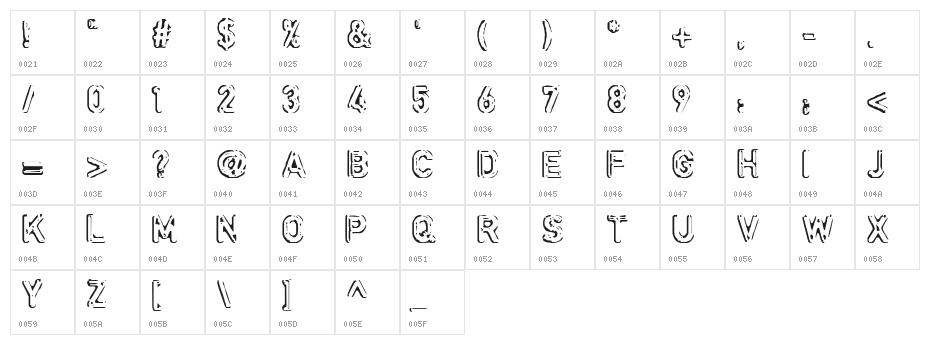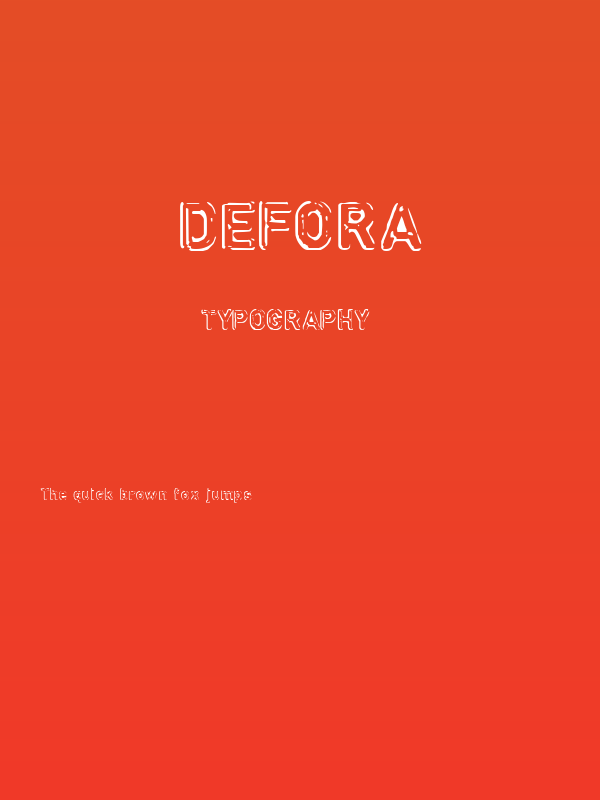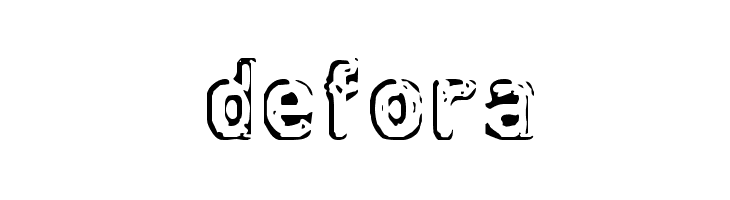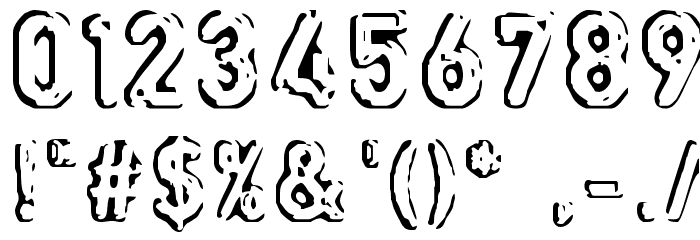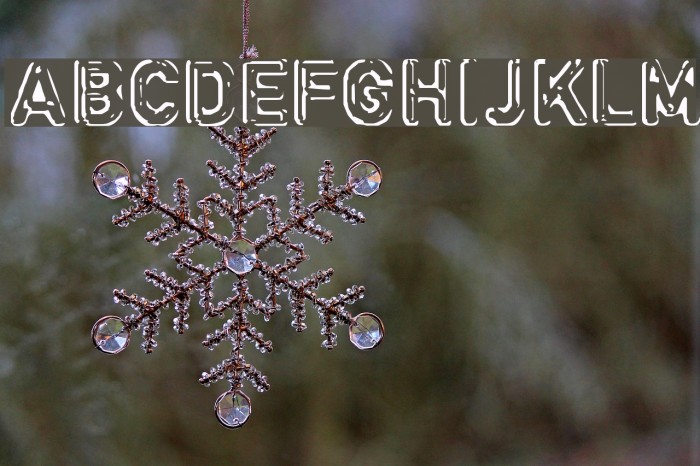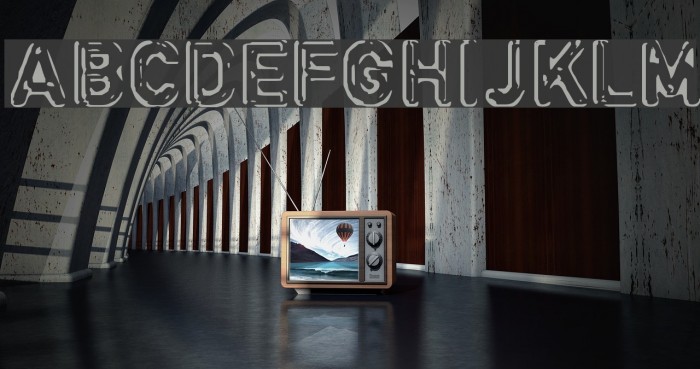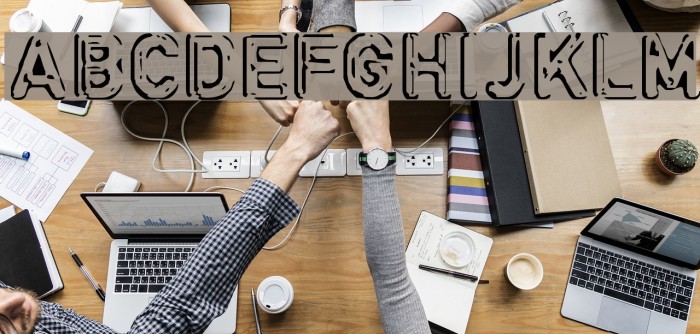
defora Font
| Projetos propostos | Ideal for projects requiring a vintage or industrial feel, such as posters, branding for rugged products, or themed event invitations. |